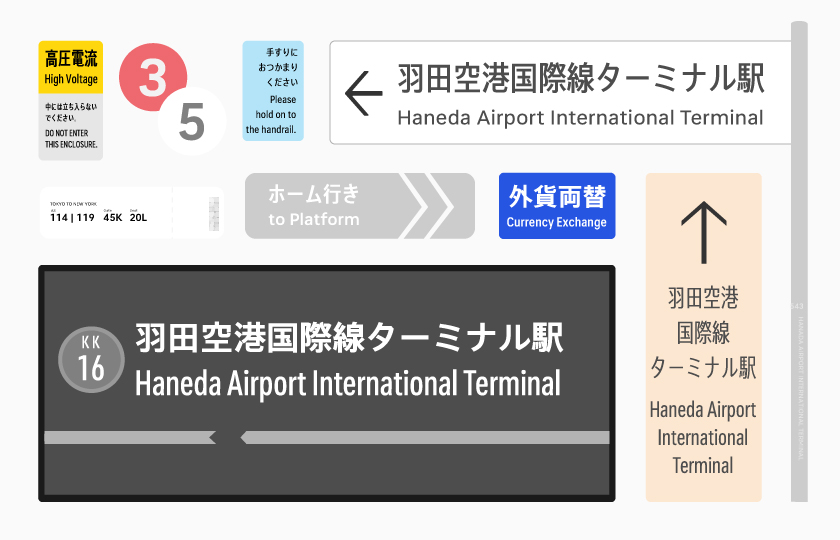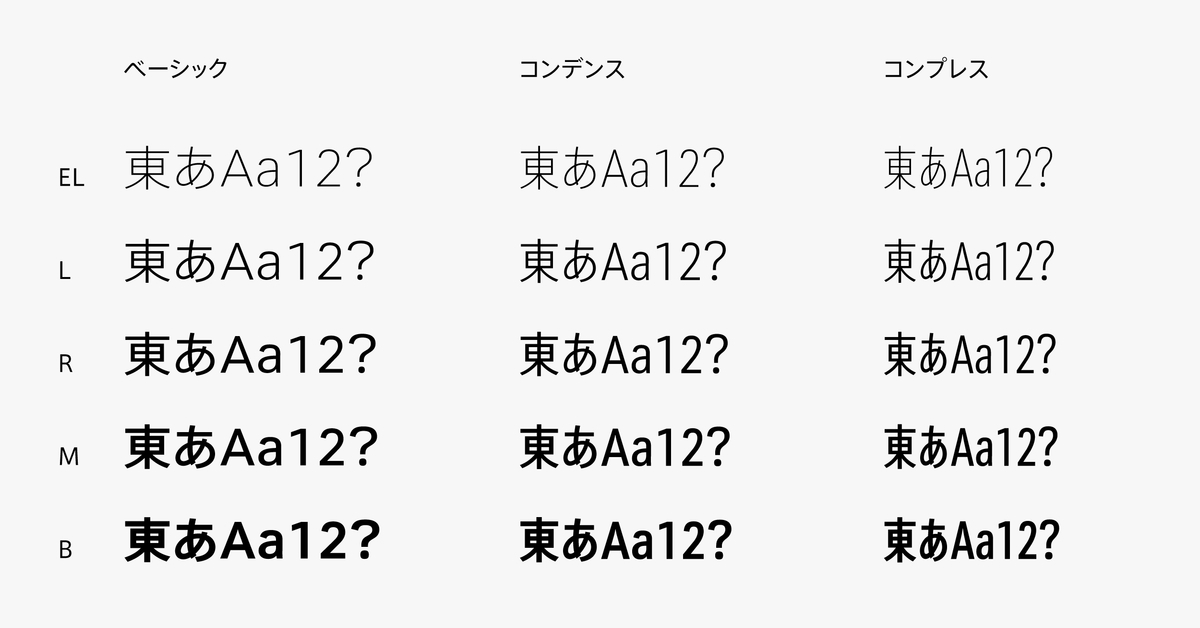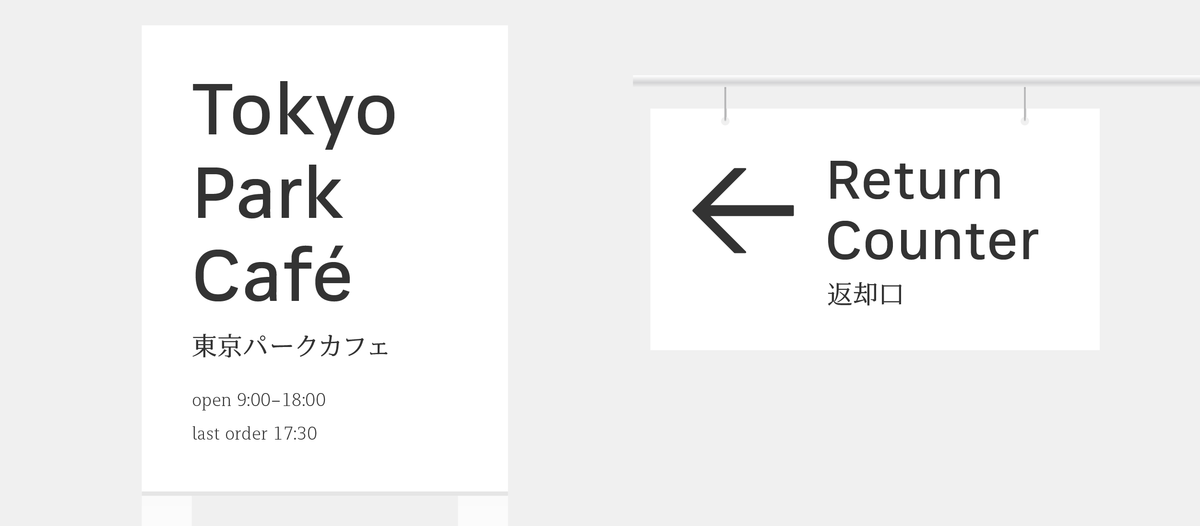
東京シティフォント
タイププロジェクトは、2020年7月1日に、都市フォントプロジェクトのひとつとして、都市空間に増えつつあるデジタルサイネージや、交通機関の案内表示などに適したフォントファミリーとして開発した「東京シティフォント」の発売を開始したことを発表した。東京シティフォントの和文部には、TP スカイローコントラストを採用し、欧文を新たに開発した。
「東京シティフォント」は、現代の情報表示に適した設計をおこない、遠距離からの判別性と表示品質の安定性を実現したフォント。和文には、視認性の高さを追求した簡潔明瞭なデザインのTPスカイローコントラストを採用。欧文には、和文の基本設計を踏まえながら、内側は直線的、外側は曲線的なスタイルで東京の建築群との相性を考慮した新しいデザインを採用している。
タイププロジェクトの代表取締役である鈴木功氏は、「都市のユーザーインターフェイスを支える情報インフラの基幹要素として、東京シティフォントを十全にご活用いただけると自負しています。また、東京シティフォントの発売で、横浜、名古屋、東京と3つの都市フォントが揃ったことをとても嬉しく思っています」と述べている。
東京シティフォントは、正体・コンデンス・コンプレスの3つのスタイルで、それぞれEL(エクストラライト)、L(ライト)、R(レギュラー)、M(ミディアム)、B(ボールド)ウエイトがあり、合わせて15フォントのファミリー構成となっている。
都市フォントプロジェクト
2010年にタイププロジェクトが発表した都市フォントプロジェクトは、都市独自のフォントをコミュニケーションツールとして活用することで、都市のアイデンティティを強化しようという試みで、2017年7月には横浜をイメージした「濱明朝」、2020年3月には名古屋をイメージした「金シャチフォント 姫」の発売を開始している。
東京シティフォント 概要
東京シティフォントの正体とコンデンスのM は、TP国立公園明朝と組み合わせることで、サインシステムの機能的な役割をさらに広げることができる。
・ウエイト: EL(エクストラライト)、L(ライト)、R(レギュラー)、M(ミディアム)、B(ボールド)